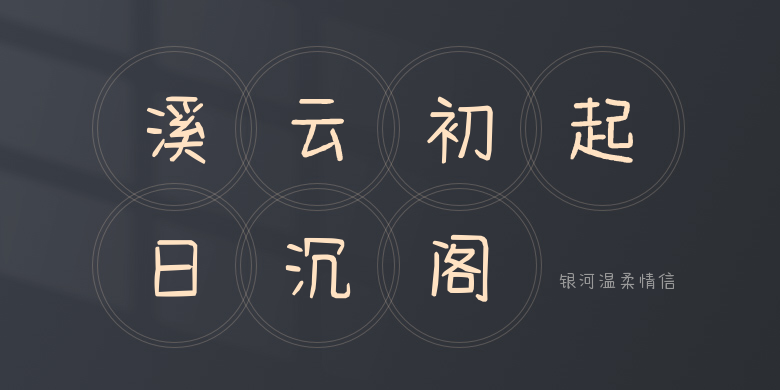
银河温柔情信
银河温柔情信,这款字体结构工整、笔画清晰,兼顾美观与易读性,适用于标题、正文、海报、包装、LOGO 等多种场景。字形优雅稳定,风格百搭耐看,适配日常排版与创意设计,让文字呈现更舒适、更具质感。银河温柔情信一笔一画,皆是细节,以均衡的比例、流畅的线条打造舒适视觉体验,字形端正大气,风格简约现代。无论是商业设计、品牌宣传还是日常排版,都能轻松驾驭,让文字更有格调与力量。银河温柔情信字体下载。